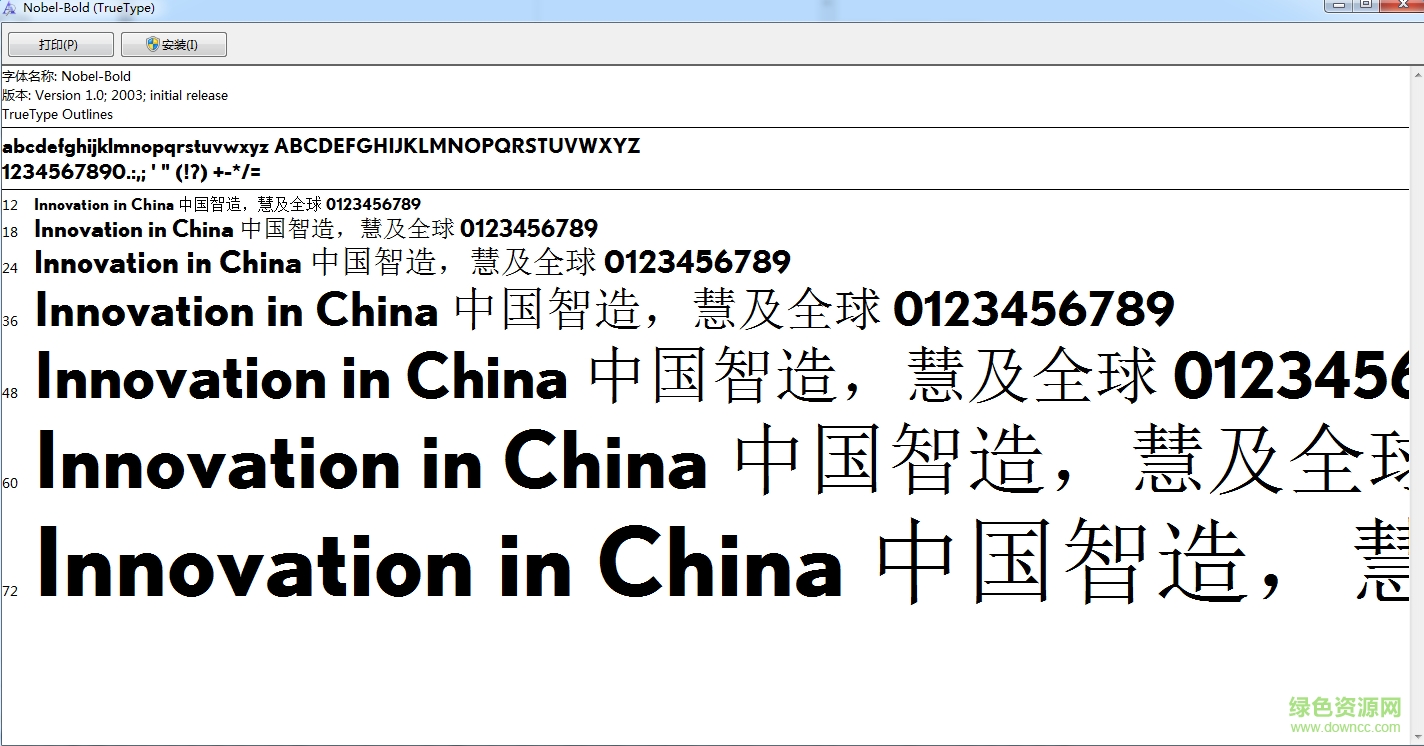
nobel book字體是一款粗黑的英文字體,字型飽滿,字體線條勻稱,結(jié)構(gòu)端正,常常用于裝飾、宣傳或各類標(biāo)題用字,需要的小伙伴快來綠色資源網(wǎng)下載吧!
nobel book字體在字形設(shè)計(jì)上采用了“黑體”的基本筆形,氣勢雄健,流暢灑脫,時(shí)代氣息十足,宜用于文章、報(bào)刊的大標(biāo)題!